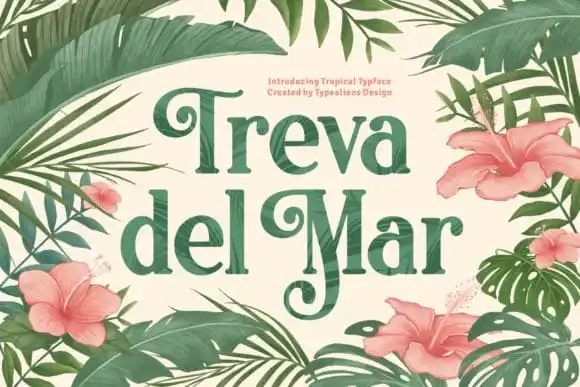
Treva Del Mar Serif Font – Download Grátis
A Treva Del Mar Serif é uma elegante tipografia serif que carrega uma atmosfera vintage para uso no tipo em tela. Seu design inovador e detalhado, disponível com mais de 450 caracteres distintos e alternativos, foi criado pelo designer typealiens a partir do site 99designs. Esta fonte é perfeita para projetos que desejam capturar um charme antiquado, combinando elegância moderna com um toque nostálgico. Suas características vão desde caracteres de texto tradicionais até alternativas e símbolos decorativos. A Treva Del Mar não apenas oferece uma experiência visual única, mas também eleva qualquer projeto para um nível superior. Com a fonte Treva Del Mar Serif, você pode criar mensagens que se destacam, criando experiências de design memoráveis e sofisticadas.